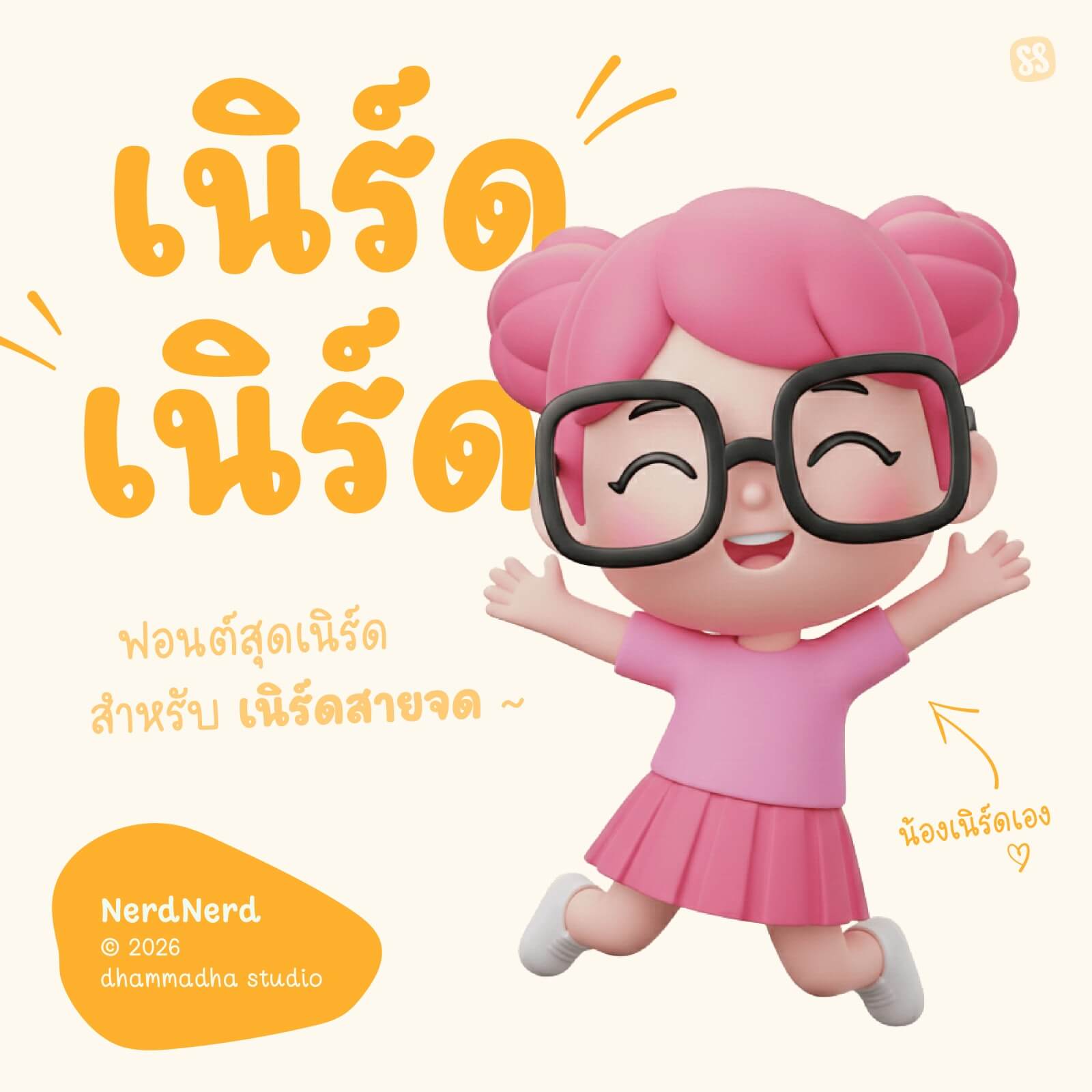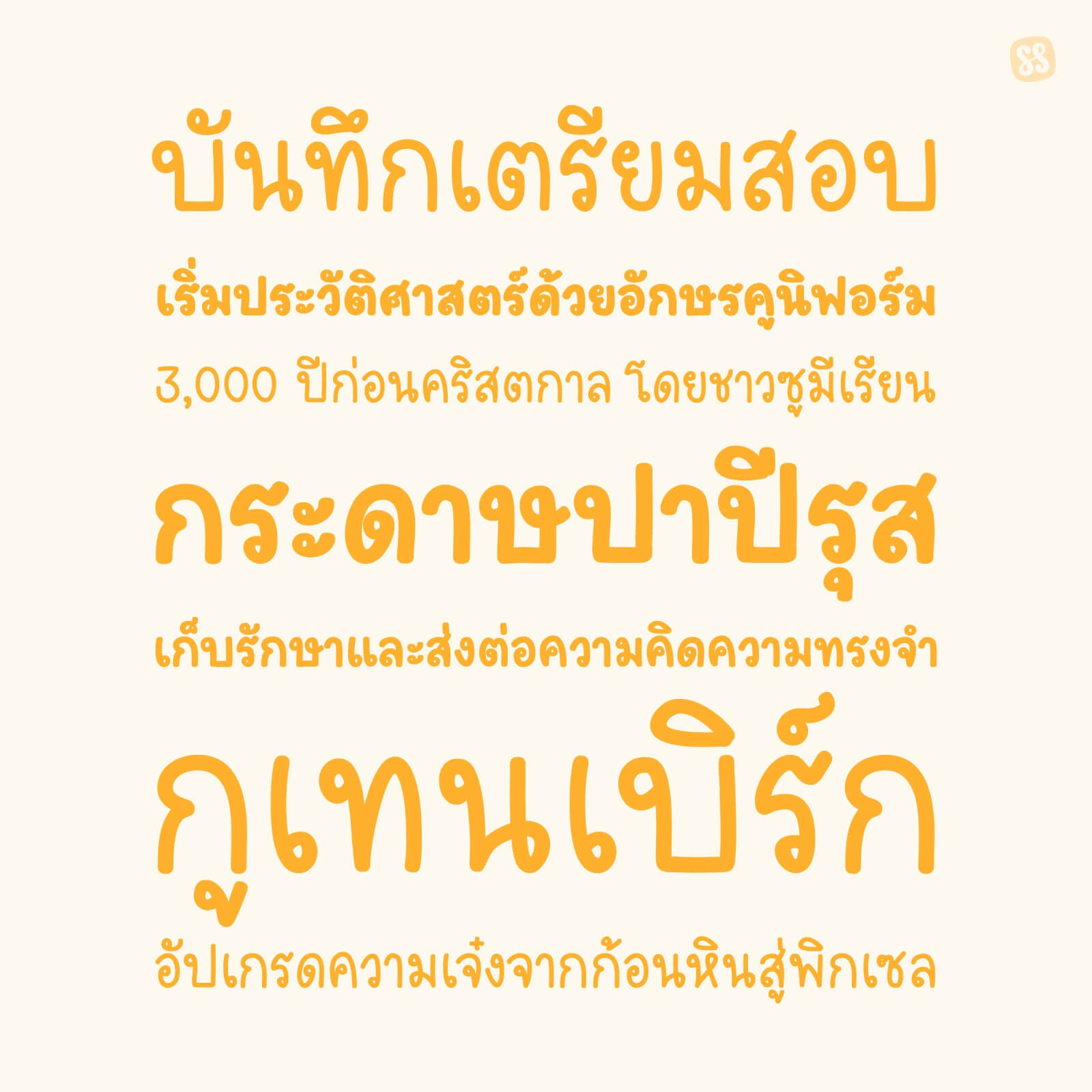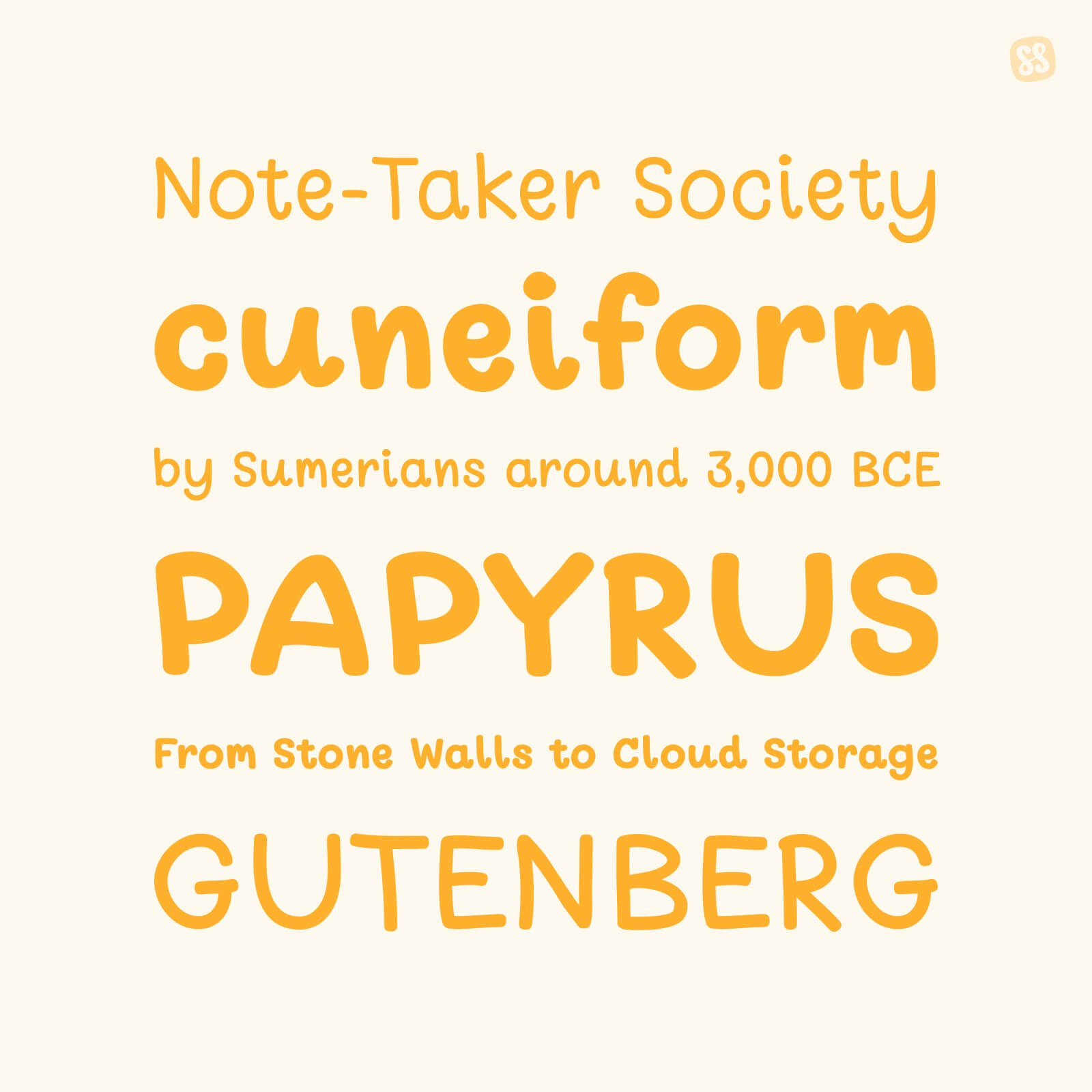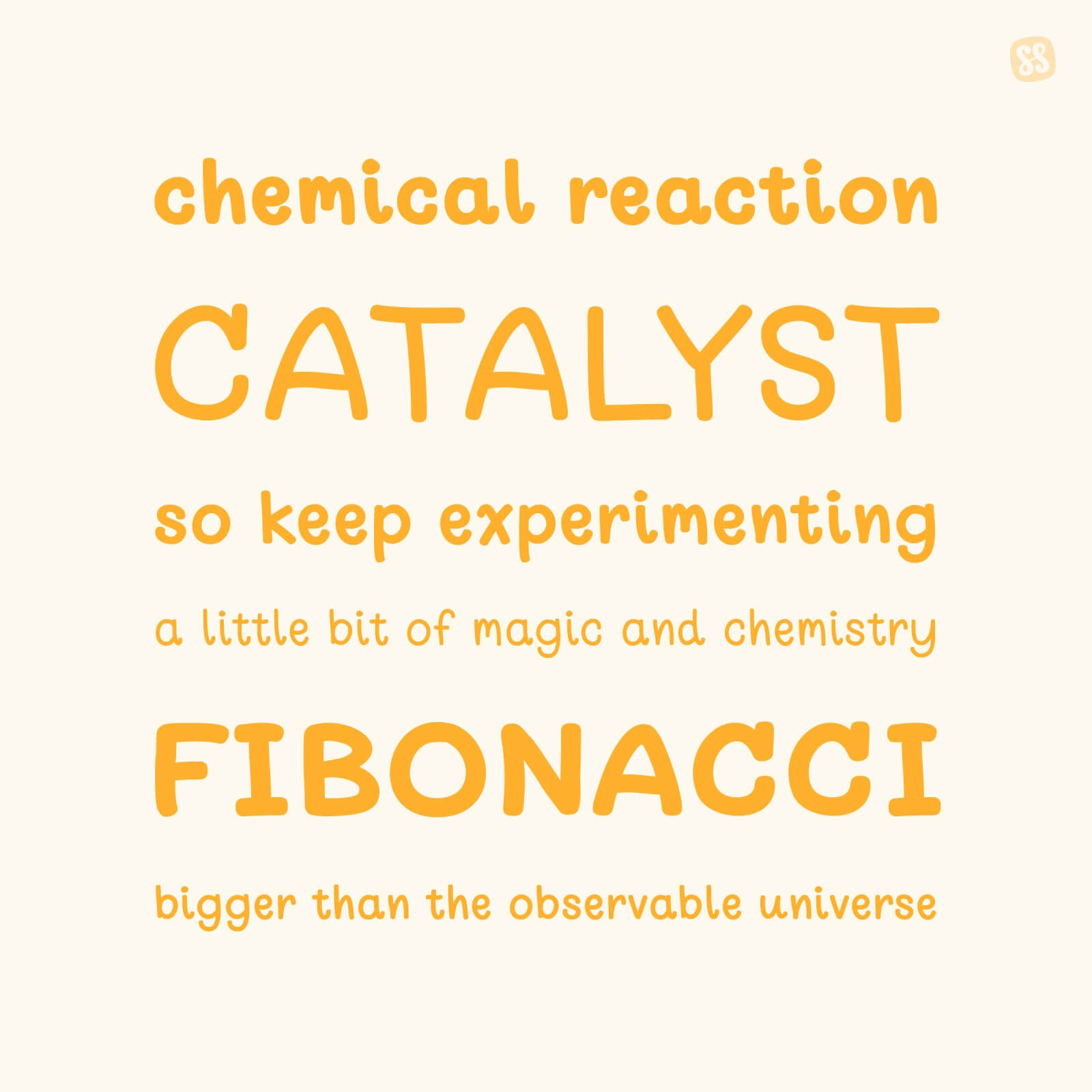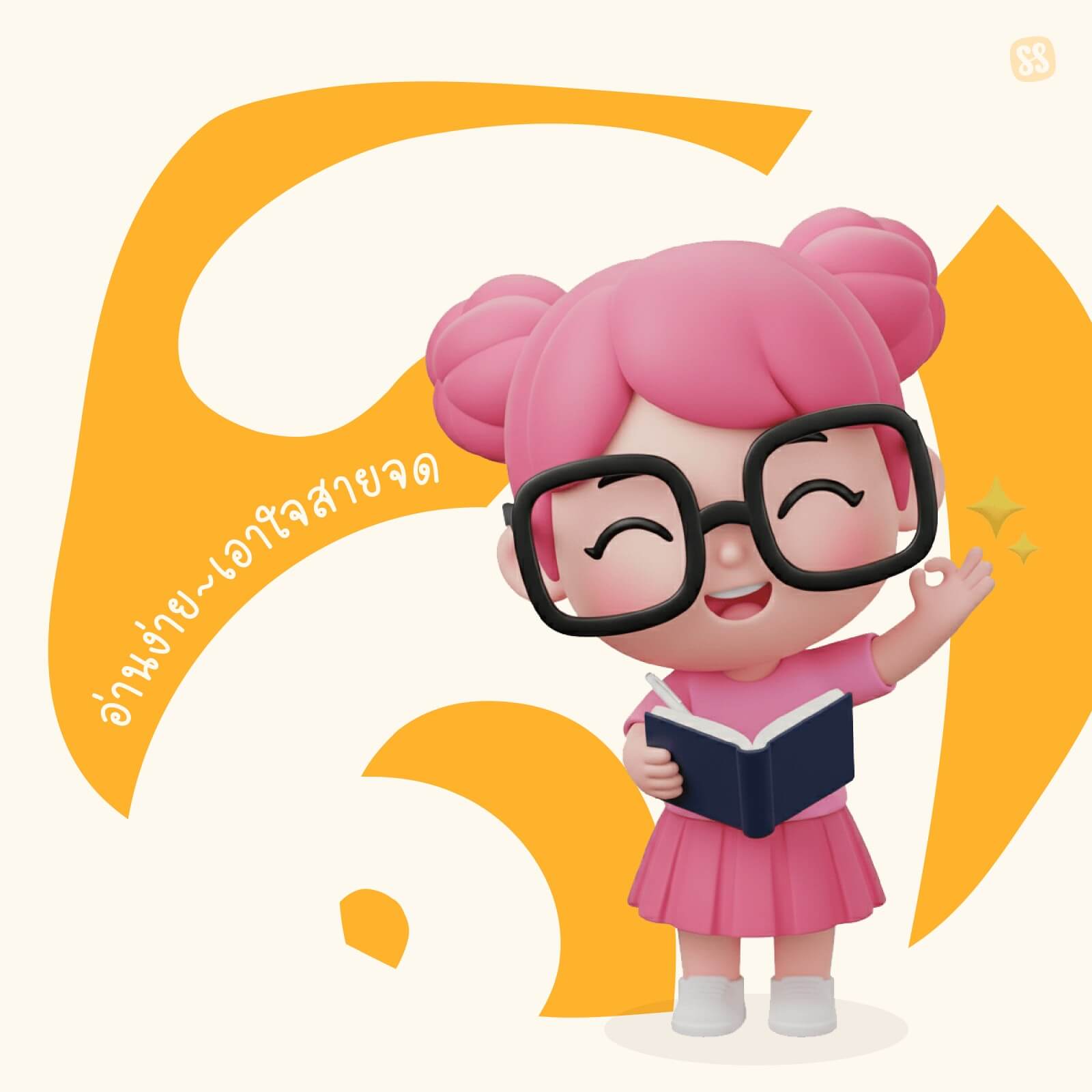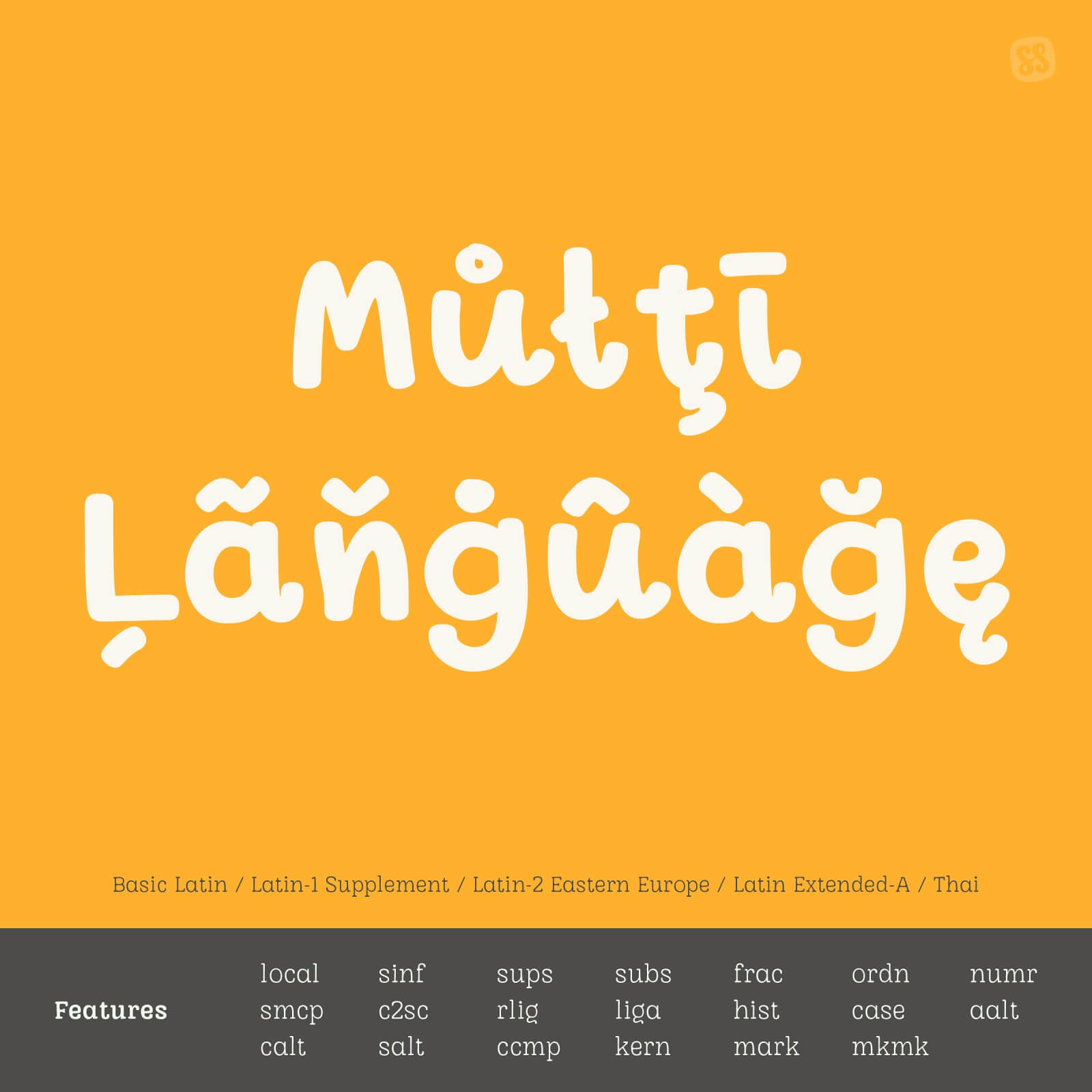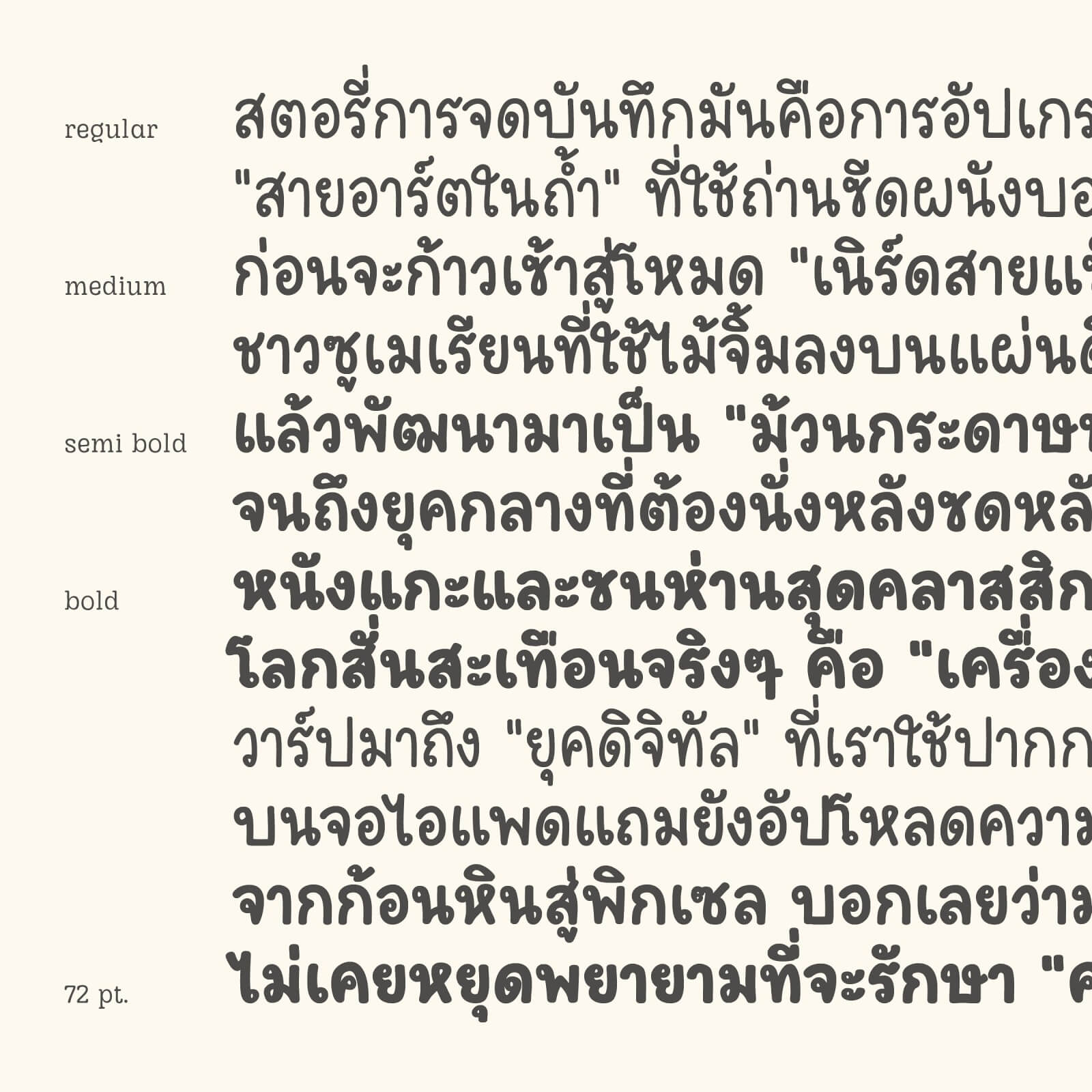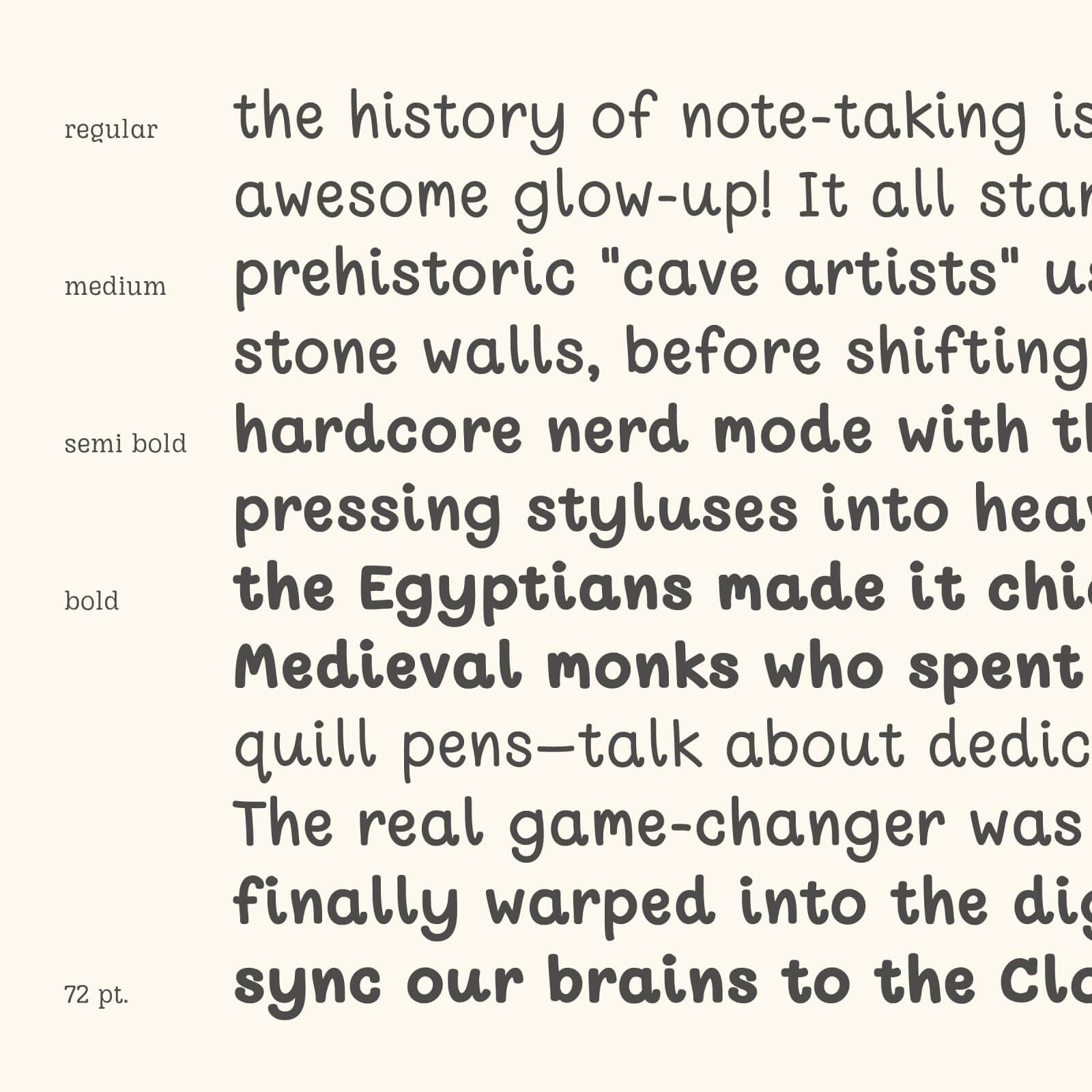
เนิร์ดเนิร์ด | NerdNerd
เบื่อไหม? จดสรุปทีไรลายมือไม่เคยรักดี… มาเปลี่ยนโน้ตให้น่าอ่านระดับ 10/10 ด้วยฟอนต์ “เนิร์ดเนิร์ด | NerdNerd” ฟอนต์สุดเนิร์ดสำหรับเนิร์ดสายจด !
4 น้ำหนักจัดเต็ม ตั้งแต่ Regular ผอมบาง ไปจนถึง Bold แบบหนาตะโกน
จะทำหัวข้อใหญ่หรือเนื้อหาจิ๋ว ๆ ก็เอาอยู่ทุกเลย์เอาต์ !
อ่านง่าย สบายตา ดีไซน์มาเพื่อเอาใจสายจดสรุปเตรียมสอบโดยเฉพาะ
อ่านทวนกี่รอบก็ไม่มีเบื่อ แถม Vibe ดีมีความเนิร์ด
ให้ฟีลลิ่ง ‘Smart & Cute’ เหมือนมีเพื่อนเรียนเก่งมาช่วยจดสรุปให้ถึงที่ !